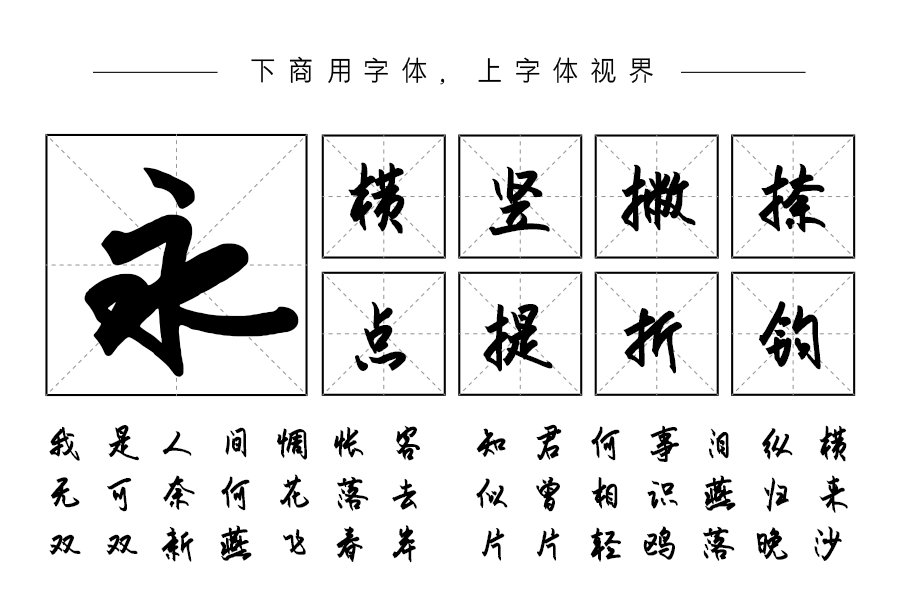
手绘板现代行书字体字库-安景臣手绘板行书
安景臣手绘板行书是一款采用手绘板进行创作的现代行书字体字库。一般的字体字库,都是由字体设计师用传统毛笔、硬笔等在普通纸上创作完成。而此款字库由作者在手绘板上绘制,难度增加了许多。不但要有高超的书写技巧,过硬的书写功力,还要掌握手绘板使用绘制方法,懂得设计相关知识。因此,手绘板字体极为罕见,好的手绘板字体更是凤毛麟角。此款字体采用手绘板绘制,既有传统书法特色,又有现代设计风貌,是一款不可多得的书法字库。
安景臣手绘板行书